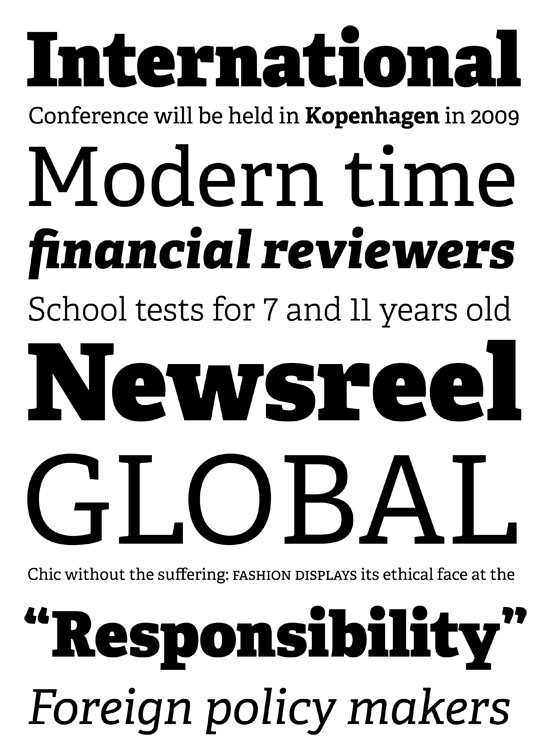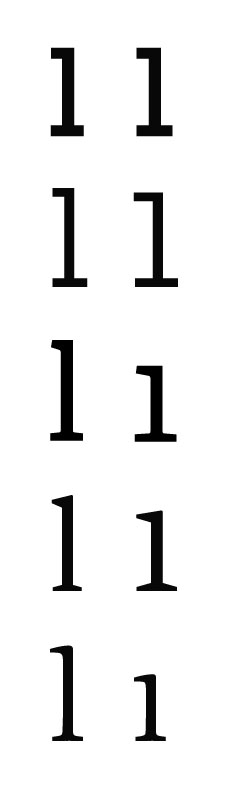
Adelle (Type Together)
While Adelle is a slab serif typeface conceived specifically for intensive editorial use, mainly in newspapers and magazines, its personality and flexibility make it a real multiple-purpose typeface. The intermediate weights deliver a very legible and neutral look when used in text sizes, providing the usual robustness expected in a newspaper font. The unobstrusive appearance, excellent texture and slightly dark color allow it to behave flawlesly in continuous text setting, even in the most demanding editorial applications.
As it becomes larger in print, Adelle shows its personality through a series of meassured particularities that make it easy to remember and identify. It has 12 styles, ranging from light to heavy, with more than 900 characters per font. Its energetic character, so inherent to slab serif fonts, becomes evident as the typeface is used for subheadings and headlines.
Auch wenn's "Slab Serif" ist - man sollte doch ein l von einer 1 unterscheiden können. Ansonsten sieht die irgendwie "nicht neu" aus ...
Ich hab keine Probleme l & 1 zu unterscheiden.
Die 1 ist deutlich breiter und hat ausgeprägtere
Serifen ... ansonsten haut sie mich aber auch
nicht gerade um!
mir gefällt sie auch auf Anhieb, auch wenn ich die Grundlinienserifen einen Tick zu dünn finde. Die Adelle vereint ganz charmant das Beste aus Scala Sans, Meta und der Bahnschrift mit Franklin Gothic oder sowas. Eine echte Alternative.
Das ist aber auch nur im täglichen Leben so, weil man sich die Bedeutung normalerweise erschließen kann. In der Genetik z.B. sind Genbezeichnungen immer eine Zusammensetzung aus Buchstaben und Zahlen. RAD1, RAD51, MPH1, sgs1, srs2 etc. Wie sieht’s bei einer solchen Ähnlichkeit jetzt bei »ClpX« aus? »H1N5«? »mlh1«? Abgesehen davon, daß man den Unterschied bei der Georgia sofort sieht: Da erschließt sich nix, entweder man weiß es oder man weiß es nicht und wenn man es nicht weiß, dann hilft, zumindest im Fließtext, nur der Griff zur Lupe um das zu identifizieren. Ich kriege immer den Koller bei sowas (Sensibilisierung nennt man das wohl); entweder man macht es gleich richtig oder man läßt es bleiben! :twisted:
Abgesehen davon, daß man den Unterschied bei der Georgia sofort sieht: Da erschließt sich nix, entweder man weiß es oder man weiß es nicht und wenn man es nicht weiß, dann hilft, zumindest im Fließtext, nur der Griff zur Lupe um das zu identifizieren.
Ich weiß nicht was ihr habt! Die Adelle bringt vier verschiedene
Ziffernsätze mit und wenn man nicht gerade die Tabellenziffern
im Fließtext verwendet sind l und 1 durchaus auch ohne Lupe
zu unterscheiden.
Tja, dann einfach mal eine Diskussion zu einem interessanten Thema starten!
Wenn alle ständig warten, dass jemand anderes anfängt …
Man muss ja auch nicht immer alles mitlesen. Einfach die interessanten Themen abonnieren (Button rechts unten) und die anderen mit » Alle Foren als gelesen markieren« abhaken.
so eine schrift ist ja auch erstmal nix für den fließtext, sondern eher für headlines und display anwendungen. finde ich.
Ich weiß daß das öfters vorkommt, mit so einem sch :| muß ich mich dann herumärgern. Gill Sans ist noch viel schlimmer.
Natürlich kann man eine Schrift so konzipieren, daß sie sich für bestimmte Zwecke dann nicht einsetzen läßt. Gerade für eine Schrift, die für Magazin-Typografie und Zeitungen eingesetzt werden soll, ist aber doch die Frage, warum man es denn eingrenzen sollte. Ich habe da wenig Sympathie. Für den Display-Bereich ist’s ja noch mal etwas anderes, keine Frage.